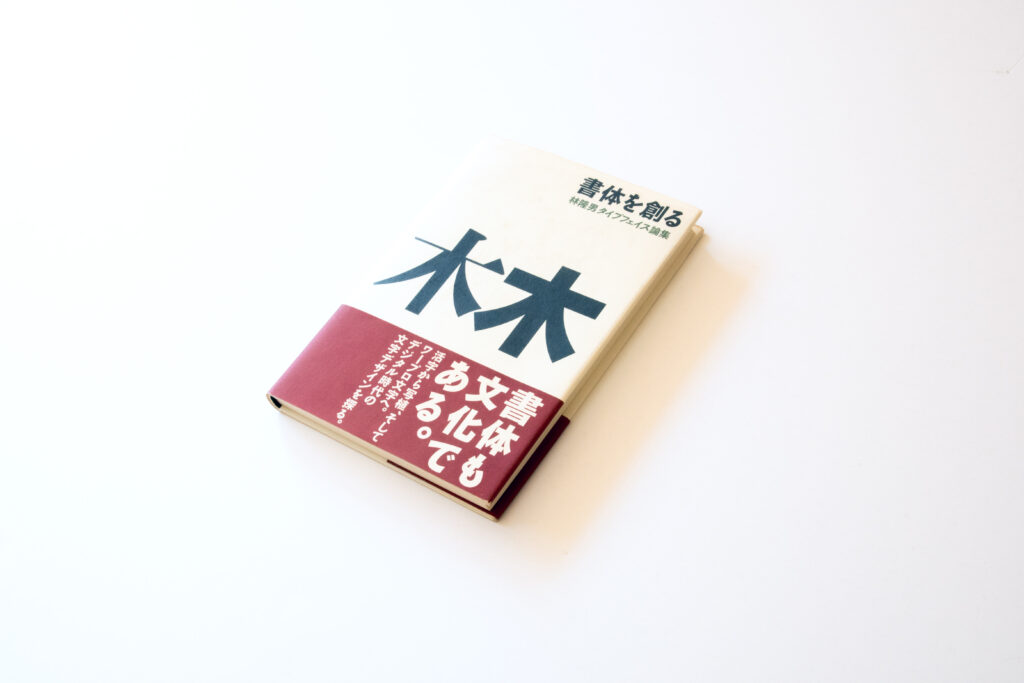
TPの書庫から『書体を創る』
今回は、林隆男著の『書体を創る 林隆男タイプフェイス論集』を紹介します。
本書はタイプバンクの創立者、林隆男さんの追悼として刊行された一冊です。雑誌などに寄稿された書体に関する林さんの論文やインタビューと、親交の深かったデザイナーなど数々の人物から林さんへ寄せられた文章で構成されています。
論集は、フォントの基礎、書体の保護について、またデザインの側面からのみならず、印刷など出力や書体制作の技術の側面からのデジタルフォントの品質についてなど多岐に渡ります。 ディレクターとしてデザイナーに対してどのような書体を作るべきかの要求が書かれた項目や、長い年数を耐えうる書体の必要性について繰り返し書かれている点、また林さんへ寄せられた文章からも文字に対する厳しい目や姿勢が窺えます。 書体の著作物としての保護の章では、書体が著作物として認められず軽視されることなく良い書体が自由に流通できるように尽力された側面も知りました。使う側や人々の生活にもたらされる文字がどうあるべきなのかを考えるのに今に通じることばかりで、現在の文字に携わる人へ向けられているものだと思いました。
続いて『書体を創る 林隆男タイプフェイス論集』に関連して弊社の鈴木から選書へのコメントです。
書体デザイナーになった当初から、書体をデザインする能力より書体をディレクションする能力のほうが稀少ではないかと感じていた。じっさい書体をつくってみないと気づけないことはたくさんあるが、書体をプロデュースしてヒットさせるむずかしさはまた別の次元にある。大きな見取り図を描いたり、俯瞰して書体デザインを見る能力を養う必要があるのではないか、そんなことをおぼろげながら考えはじめた頃、林隆男さんの存在を知った。
『書体を創る』と『味岡伸太郎 書体講座』を合わせて読むことで、日本語書体の課題を再点検できるだろう。
味岡伸太郎さんは、いうまでもなく仮名書体「良寛・小町」のデザイナーである。書と書体デザインをつなぎ、設計思想を自分の言葉で語る稀有な存在だ。本書には氏の考えかたが凝縮されている。
『書体を創る 林隆男タイプフェイス論集』
著者:林隆男
発行:ジャストシステム